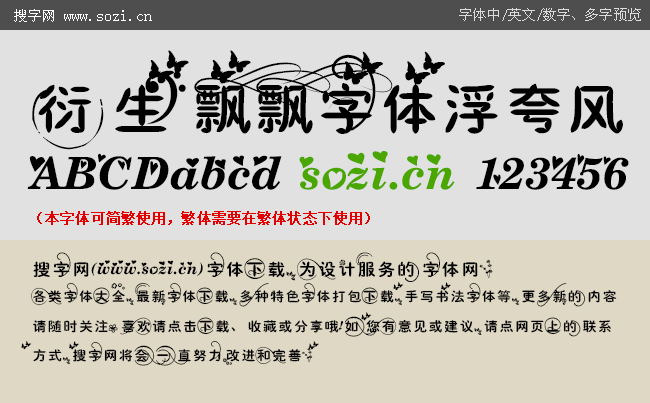
衍生飄飄字體浮夸風(fēng)
搜字網(wǎng)給大家提供一款很可愛的手機(jī)中文字體下載。字體名叫衍生飄飄字體浮夸風(fēng),這款手機(jī)字體是以橄欖體為原形,筆畫間插入了漂亮的卡通花紋圖案。橄欖字體以橄欖為原形而設(shè)計(jì),線條粗壯,大方得體,充滿趣味性,特別適合喜歡手機(jī)字體個(gè)性一些的朋友在手機(jī)上安裝使用。